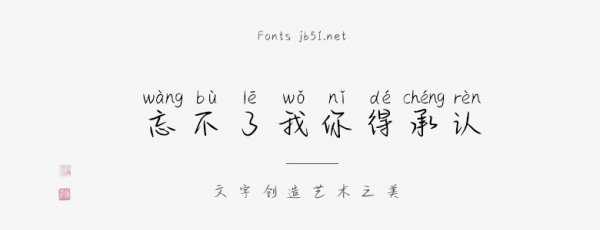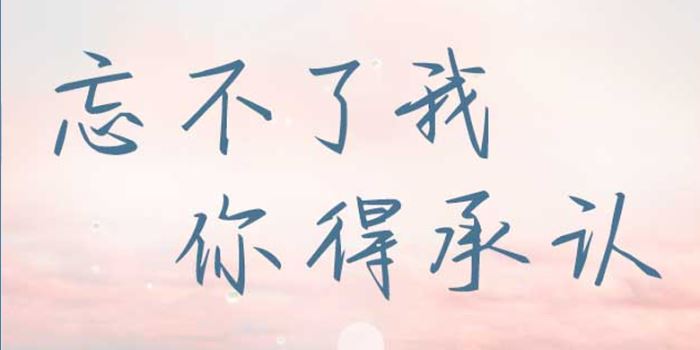
方正手迹-忘不了我你得承认
方正手迹-忘不了我你得承认由方正字库余丹设计师出品的艺术字体,该字笔画锋利尖锐,给人一种侠客的感觉,适合应用于艺术设计、平面宣传设计、网页设计,书法等领域。
忘不了我你得承认这款字是一款潇洒的手写行书字体。笔画锋利尖锐,给人一种侠客的感觉。整体潇洒硬朗。适用于文艺类的书刊、品牌广告和产品包装设计,以及社交网络的个性化用字。